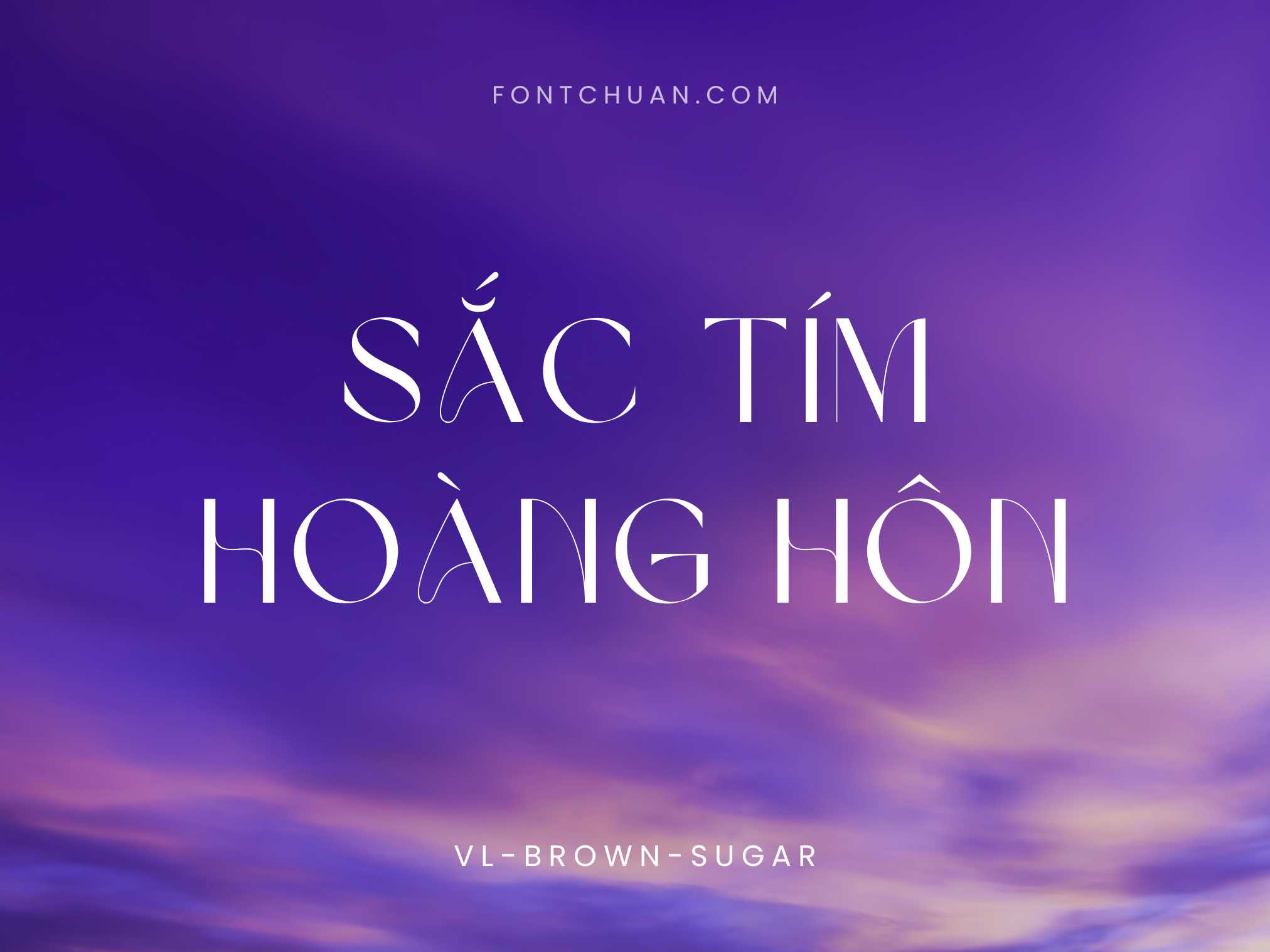
Font VL Brown Sugar Việt Hóa
VL-Brown-Sugar là một phông chữ serif mang phong cách hiện đại và tinh tế, được thiết kế bởi Muntab_Art. Phông chữ này bao gồm các chữ cái in hoa, chữ số và nhiều dấu câu, phù hợp cho các thiết kế như áp phích, trang web, thương hiệu, minh họa và huy hiệu. VL-Brown-Sugar đã được Việt hóa bởi Việt Linh, hỗ trợ đầy đủ các ký tự tiếng Việt, giúp người dùng dễ dàng sử dụng trong các dự án sáng tạo. Phông chữ này được thành viên Font Chuẩn sưu tầm và đăng tải nhằm phục vụ nhu cầu thiết kế đa dạng.
Với thiết kế thanh lịch và rõ ràng, VL-Brown-Sugar phù hợp cho các ứng dụng như tiêu đề, văn bản dài, thiết kế logo và các ấn phẩm in ấn. Trong lĩnh vực sự kiện, phông chữ này có thể được sử dụng trong các dịp như lễ cưới, hội nghị và các sự kiện văn hóa. Ngoài ra, VL-Brown-Sugar cũng thích hợp cho các ngành nghề như quảng cáo, giáo dục và công nghệ.